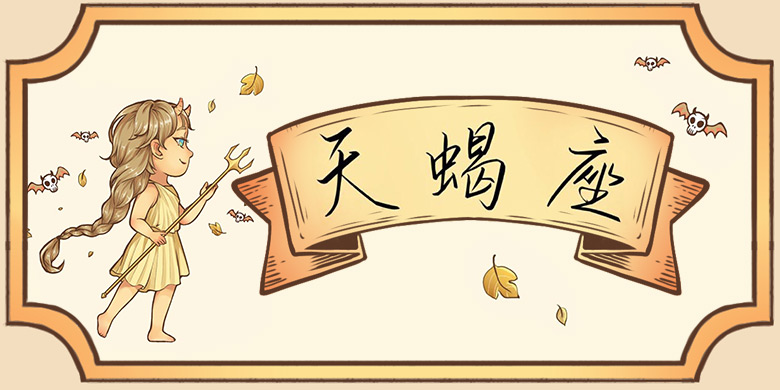
方正手迹-腹黑高冷-天蝎座
字体品牌: 方正手迹 设计师:王航 字体分类:常规书写·硬笔 字体属性:精品字 字符集:简繁扩展(GBK) 发布时间: 2019
腹黑高冷-天蝎座是一款风格鲜明的手写体,笔画锐利出笔锋,转折略微坚硬,整体字体有一种自带的风骨感。适用于文艺类的书刊、品牌广告和产品包装设计,以及社交网络的个性化用字。